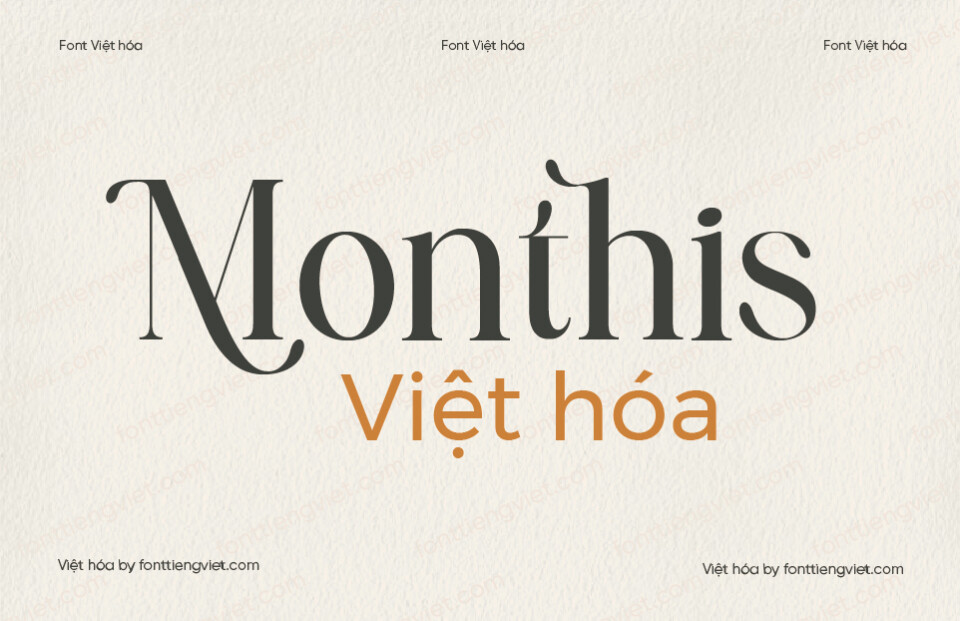
Font Việt hóa 1FTV VIP Monthis
Font Việt hóa 1FTV VIP Monthis – Lựa chọn hoàn hảo cho thiết kế thanh lịch
Giới thiệu về Font Việt hóa 1FTV VIP Monthis
Trong thế giới thiết kế đồ họa hiện nay, việc lựa chọn một bộ font chữ phù hợp đóng vai trò quyết định đến sự thành công của một tác phẩm. Font Việt hóa 1FTV VIP Monthis nổi lên như một hiện tượng nhờ sự kết hợp tinh tế giữa nét đẹp cổ điển và hơi thở hiện đại. Đối với các bạn học sinh và giáo viên, việc sử dụng một Font Miễn Phí chất lượng như Monthis sẽ giúp các bài thuyết trình, báo cáo hay thiệp mời trở nên chuyên nghiệp và thu hút hơn bao giờ hết. Bộ font này không chỉ sở hữu các đường nét uyển chuyển mà còn được tối ưu hóa hoàn toàn cho bảng mã tiếng Việt, giúp loại bỏ triệt để các lỗi hiển thị dấu câu khó chịu thường gặp ở các bộ font ngoại nhập.
Đặc điểm nổi bật của Font Việt hóa 1FTV VIP Monthis
Thiết kế Serif hiện đại và sang trọng
Font Việt hóa 1FTV VIP Monthis thuộc dòng Serif (phông chữ có chân) nhưng được cải tiến với độ tương phản giữa các nét thanh và nét đậm cực kỳ hài hòa. Điều này tạo nên một cảm giác vừa trang trọng, vừa gần gũi, rất phù hợp cho các dự án đòi hỏi tính thẩm mỹ cao như bìa sách, logo thương hiệu thời trang hoặc các ấn phẩm văn phòng trong trường học. Các ký tự được chăm chút tỉ mỉ, đảm bảo tính dễ đọc ngay cả khi sử dụng ở kích thước nhỏ, giúp người xem không bị mỏi mắt khi theo dõi nội dung dài.
Khả năng tương thích và ứng dụng linh hoạt
Một điểm cộng lớn của Font Việt hóa 1FTV VIP Monthis chính là khả năng ứng dụng đa dạng trên nhiều phần mềm thiết kế khác nhau như Photoshop, Canva, Illustrator hay ngay cả trong Microsoft Word và PowerPoint. Với bộ ký tự đầy đủ các dấu tiếng Việt được đặt đúng vị trí, bạn có thể tự tin sáng tạo mà không lo lắng về vấn đề tương thích kỹ thuật. Font chữ này đặc biệt hiệu quả khi dùng làm tiêu đề (Heading) để tạo điểm nhấn hoặc dùng cho các đoạn trích dẫn quan trọng, mang lại vẻ đẹp thanh thoát cho tổng thể trang giấy.
Lý do nên sử dụng Font Việt hóa 1FTV VIP Monthis trong học tập
Nâng tầm bài giảng và báo cáo dự án
Đối với môi trường giáo dục, việc trình bày nội dung một cách khoa học và đẹp mắt là rất quan trọng. Sử dụng Font Việt hóa 1FTV VIP Monthis giúp các bạn học sinh rèn luyện tư duy thẩm mỹ và sự chỉn chu trong từng sản phẩm học tập. Thay vì sử dụng những phông chữ mặc định nhàm chán, việc thay đổi sang bộ font VIP này sẽ khiến thầy cô và bạn bè ấn tượng ngay từ cái nhìn đầu tiên. Ngoài ra, tính năng hiển thị ổn định của nó cũng giúp việc in ấn tài liệu học tập trở nên sắc nét, không bị nhòe hay mất nét.
Sáng tạo thiệp và ấn phẩm sự kiện trường học
Trong các dịp lễ hội hay sự kiện tại trường, Font Việt hóa 1FTV VIP Monthis là người bạn đồng hành lý tưởng để thiết kế các mẫu thiệp chúc mừng, bằng khen hay banner trang trí. Sự mềm mại của các đường cong trong bộ font này mang lại cảm giác ấm áp và chân thành, rất phù hợp để gửi gắm những lời tri ân. Bạn có thể kết hợp nó với các tông màu pastel hoặc màu trầm để tạo ra những tác phẩm đậm chất nghệ thuật mà vẫn giữ được sự tinh tế cần thiết.
Kết luận về bộ Font Việt hóa 1FTV VIP Monthis
Tóm lại, Font Việt hóa 1FTV VIP Monthis không chỉ đơn thuần là một công cụ hỗ trợ gõ chữ mà còn là nguồn cảm hứng bất tận cho những ai yêu cái đẹp và sự hoàn mỹ. Việc lựa chọn được một bộ font vừa miễn phí lại vừa được Việt hóa chuẩn xác là một điều tuyệt vời cho cộng đồng thiết kế Việt Nam. Hy vọng rằng với những chia sẻ trên, bạn sẽ có thêm một lựa chọn chất lượng để làm đẹp cho các dự án cá nhân của mình. Hãy nhanh tay trải nghiệm Font Miễn Phí, Font Việt Hóa, Font Việt hóa 1FTV VIP Monthis để cảm nhận sự khác biệt vượt trội trong từng đường nét thiết kế.